デザイナーじゃないのに、急に会社で名刺やポスターの作成をすることになって「イメージ通りに仕上がらない…」と困っていませんか?
今回はそんなときに役立つ失敗しないフォントの選び方を解説します。
スタイル別でおすすめフォントも紹介しているので、マネするだけで簡単に演出したいイメージを表現できます。時間がない方でもフォントを変えるだけで出来上がりの印象が大きく変わるので、デザインに迷った時はぜひ参考にしてみてください。
基本のフォントの種類と与えるイメージ
フォントの選び方をご紹介する前に、まずはよく使われている基本のフォントと与えるイメージについて解説します。
それぞれの特徴を知ることで、イメージに合ったフォント選びがしやすくなります。
和文フォント
①明朝体(みんちょうたい)
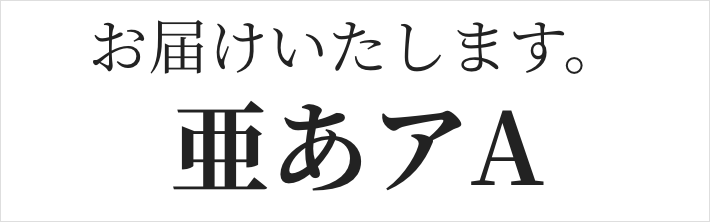
明朝体とは、楷書体(一画一画を続けずに、筆を離して書いたもの)を整理・単純化して横線を細く縦線を太くした書体の総称のことです。
「うろこ」と呼ばれる線の右端についている三角形や、「はね」「はらい」が表現されているのが特徴です。
書籍や雑誌、新聞の本文でよく用いられます。
■ 明朝体が与えるイメージ
- 落ち着き
- 日本的
- 信頼感・安心感
- 女性的
②ゴシック体
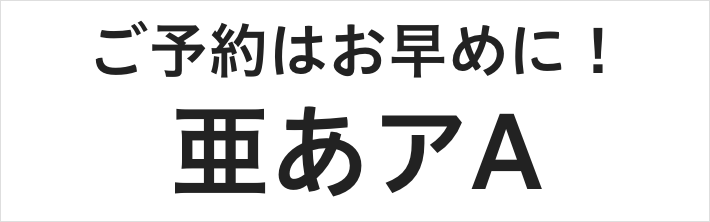
ゴシック体とは、全ての線や点画がほぼ均一の太さになるように設計された書体の総称のことです。形状が直線的なので、文字サイズが大きくても小さくても一定の読みやすさを保てることが特徴です。
ポスター、見出し、ロゴデザインなどでよく用いられます。
■ ゴシック体が与えるイメージ
- 力強い
- 現代的
- 無骨
- 男性的
③丸ゴシック体
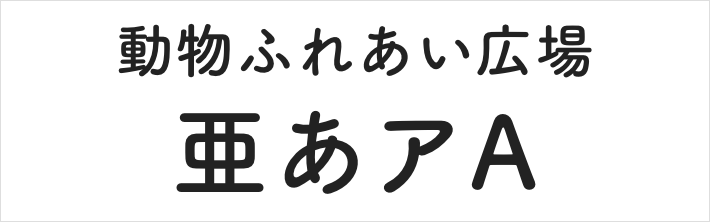
丸ゴシック体とは、ゴシック体の角を丸めた書体の総称のことです。
ゴシック体と同様の読みやすさを保ちつつ、曲線的で言葉をやわらかく見せる効果があることが特徴です。
子供向けの絵本や、かわいい印象を与えたい場合などによく用いられます。
■ 丸ゴシック体が与えるイメージ
- かわいい
- 優しい
- 温かい
- 子供っぽい
④楷書体(かいしょたい)
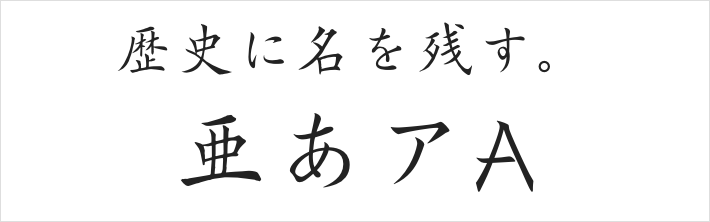
楷書体とは、字画を続けたり省略したりせずに、一画一画を書いた書体の総称のことです。
手書き文字がもとになっているため、筆使いが色濃く残っているのが特徴です。
書道の手本や、伝統・歴史を感じさせたい場合によく用いられます。
■ 楷書体が与えるイメージ
- 日本的
- 伝統・歴史
- 古代
- 中国的
欧文フォント
①ローマン体
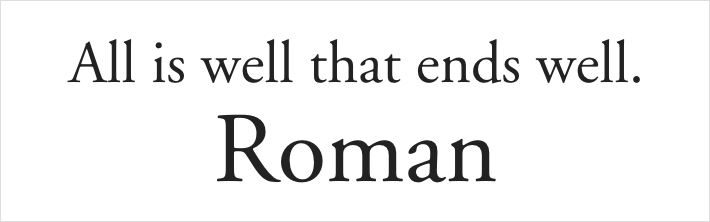
ローマン体は、エレメントの端に「セリフ」と呼ばれる爪状のデザインを持つ書体の総称のことです。大文字が古代ローマで誕生したことが名前の由来となっています。
和文フォントの「明朝体」のように欧文フォントでは最もスタンダードな書体で、幅広く用いられています。
■ ローマン体が与えるイメージ
- 歴史
- 品位
- 落ち着き
- 知的さ
②サンセリフ体
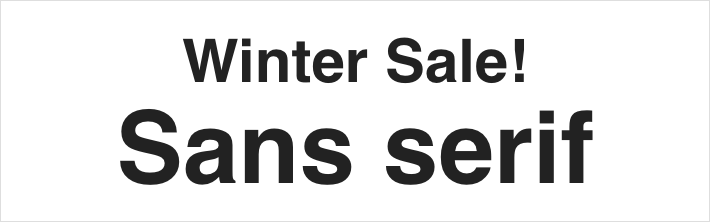
サンセリフ体とは、セリフを持たない書体の総称のことです。「サン(Sans)」はフランス語で「ない」という意味であることからこの名前になっています。
装飾の要素が少ないため、あらゆる場面で使いやすい書体です。
■サンセリフ体が与えるイメージ
- 無機質
- 現代的
- 直線的
- シンプル
③スクリプト体
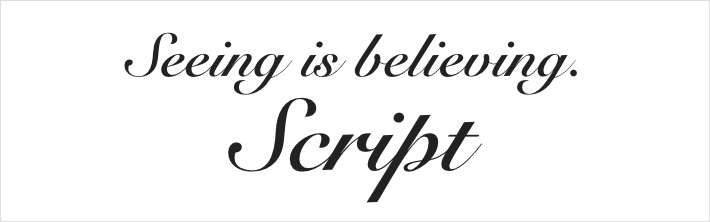
スクリプト体とは、手書きの流れを残した書体の総称のことです。ほとんどの書体が続け字になるように設計されているため、字間をあけずに使用しましょう。
ウェディングやジュエリーなどのロゴによく用いられますが、サインペンで書いたようなデザインの書体も一部あり、その場合はおもちゃ・お菓子のパッケージに向いています。
■スクリプト体が与えるイメージ
- 高級感
- 上品
- 美しい
- 女性的
④スラブセリフ体
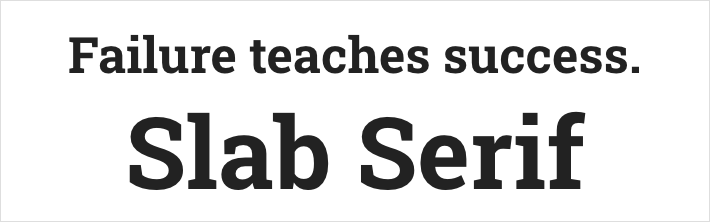
スラブセリフ体とは、ローマン体のセリフを持ちつつ、サンセリフ体の均一な太さの両方の要素を持つ書体の総称のことです。ローマン体よりもセリフが四角く厚みがあり、どっしりとした力強い印象です。目立つ書体なので、ポスターやロゴなどによく用いられます。
■スラブセリフ体が与えるイメージ
- 力強い
- 男性的
- 重い
- 安定感
スタイル別のおすすめフォント
ここからは、演出したいスタイル別にフォントの選び方について解説します。
それぞれのおすすめフォントをマネするだけでデザインのイメージに近づけられます。
01:男性的な演出
男性のイメージを演出するときは、「太さ」「重さ」「無骨さ」を重視します。
フォントを選ぶときはできるだけウエイトが太く、角ばっていて、文字の間が詰まっているものを選びましょう。
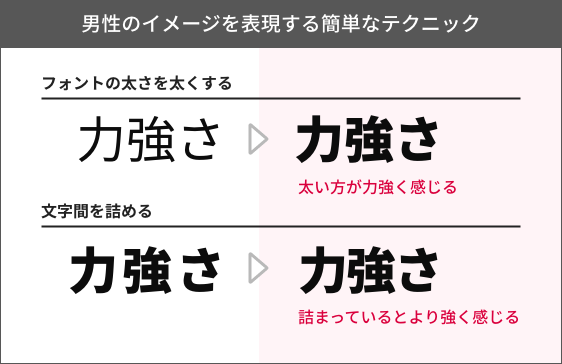
おすすめ和文フォント:M PLUS 2
(画像はBlackを使用)
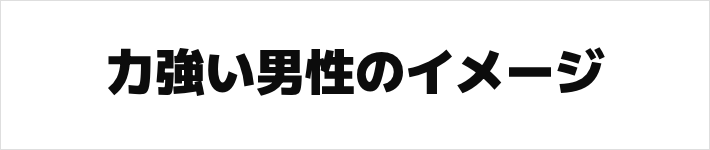
おすすめ欧文フォント:Arvo
(画像はBoldを使用)
02:女性的な演出
女性のイメージを演出するときは、「繊細さ」「やわらかさ」「曲線」を重視します。
フォントを選ぶときは曲線がきれいな明朝体や線の細い書体を選びましょう。
おすすめ和文フォント:Noto Serif Japanese
(画像はRegularを使用)
おすすめ欧文フォント:Pinyon Script
(ウエイトはRegularのみ)
03:子供っぽさの演出
子供っぽいイメージを演出するときは、「かわいらしさ」「ポップさ」「自由さ」を重視します。フォントを選ぶときは丸みがあって読みやすい書体を選びましょう。
おすすめ和文フォント:Kosugi Maru
(ウエイトはRegularのみ)
おすすめ欧文フォント:Fredoka
(画像はBoldを使用)